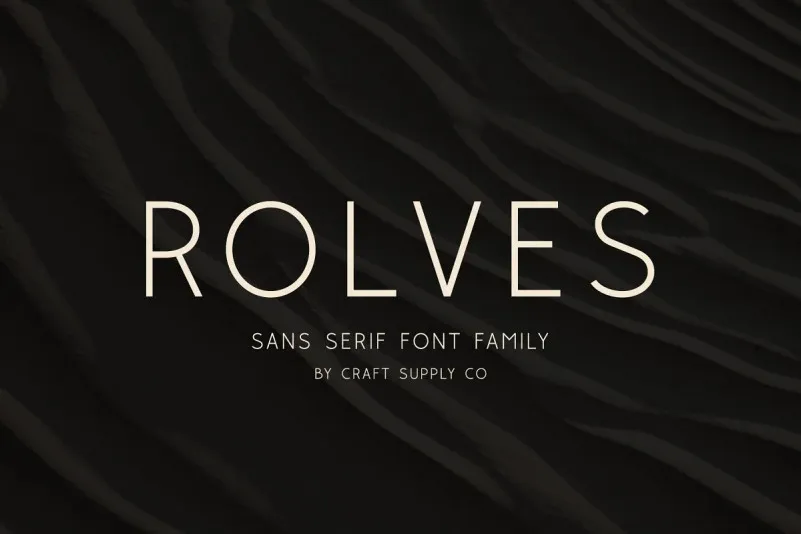
A Rolves Font é uma tipografia geométrica sem serif que destaca-se por sua simplicidade contemporânea e moderna abordagem do tipo sem serifado. Feita pelo designer de fontes Craft Supply Co., essa família de fontes possui oito estilos distintos, cada um trazendo a riqueza única de uma tipografia geométrica que se destaca em seu campo. O principal diferencial da Rolves Font está em suas linhas com baixa contraste e desenhos de letras levemente retangular. Esta característica combina-se perfeitamente para criar um design clean, minimalista e fácil de ler, sem deixar de lado a elegância do tipo geométrico. A escolha da Rolves para projetistas digitais busca oferecer uma opção versátil que se destaca não apenas pela simplicidade, mas também por sua capacidade de complementar diversos estilos e ambientes design. Com uma visão contemporânea na fonte, a Rolves abraça o mundo digital, enquanto mantém uma conexão atemporal com a história do tipo. Ideal para aplicações digitais e móveis, como aplicativos, websites ou editoriais online, essa fonte se destaca por sua capacidade de fornecer um design limpo e moderno sem esquecer dos detalhes essenciais de boa tipografia.